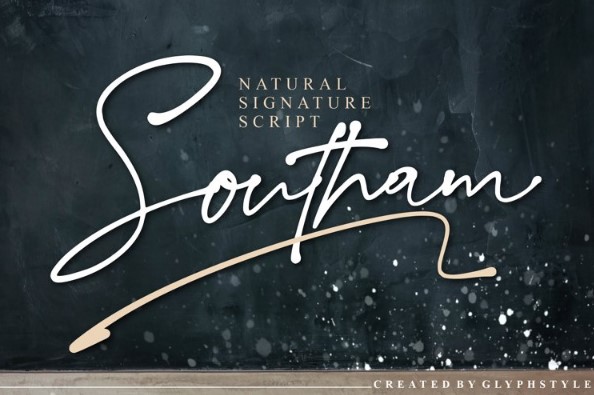
Southam - фирменный текст с чернильным стилем и естественным течением.
Элегантный шрифт с естественными царапинами от руки.
Этот фирменный шрифт идеально подходит для свадеб, водяных знаков, брендинга, например, для интервью, визитных карточек, логотипов продукции и т.д.
Southam идеально подходит для брендинговых проектов, логотипов, свадебных дизайнов, постов в социальных сетях, рекламы, упаковки товаров, дизайна продуктов, этикеток, фотографий, водяных знаков, приглашений, канцелярских принадлежностей и любых проектов, где требуется ощущение рукописной подписи.